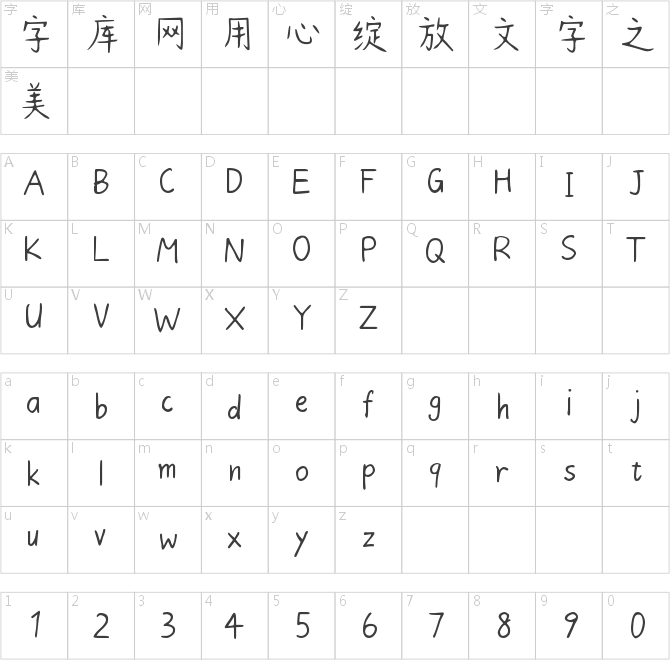
Aa糖炒小星球 詳情頁
字體名稱: Aa糖炒小星球
Aa糖炒小星球
Aa糖炒小星球字體字庫是一款讓人賞心悅目、百看不厭的中文字體,適合各類廣告和產(chǎn)品包裝設(shè)計(jì)應(yīng)用,字體大小2.91MB,格式為ttf字體,上傳用戶是Aa字庫,作者/版權(quán)方為Aa字庫